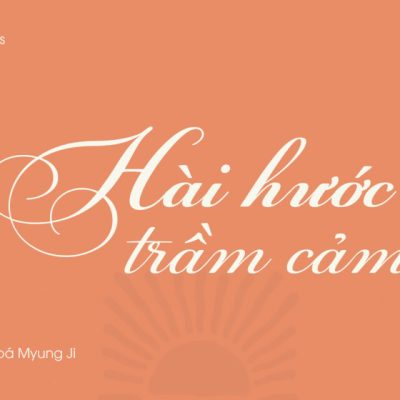
Giới thiệu về Font việt hoá MJ Monalisa
Trong thế giới đồ họa hiện đại, việc lựa chọn Font Chữ phù hợp đóng vai trò quyết định đến tính thẩm mỹ của sản phẩm. Font việt hoá MJ Monalisa là một bộ font mang phong cách script thanh lịch, tinh tế và cực kỳ sang trọng. Đây là lựa chọn hoàn hảo cho những ai đang tìm kiếm sự mềm mại nhưng vẫn giữ được nét hiện đại cho các dự án thiết kế của mình. Đặc biệt, phiên bản này đã được tối ưu hóa tiếng Việt hoàn chỉnh, giúp người dùng không còn lo lắng về lỗi hiển thị dấu.
Tại sao nên sử dụng Font việt hoá MJ Monalisa?
Bộ font này sở hữu những đường nét uốn lượn tự nhiên, tạo cảm giác như nét chữ viết tay nghệ thuật. Font việt hoá MJ Monalisa rất phù hợp để ứng dụng trong việc thiết kế thiệp mời, bìa sách, logo thương hiệu hoặc các ấn phẩm truyền thông học đường. Với khả năng tương thích cao trên nhiều phần mềm thiết kế như Photoshop, AI hay Canva, người dùng có thể dễ dàng tạo ra những tác phẩm độc đáo chỉ trong vài phút thao tác đơn giản.
Cách ứng dụng Font việt hoá MJ Monalisa hiệu quả
Để tận dụng tối đa vẻ đẹp của font, bạn nên kết hợp nó với các phông chữ không chân (sans-serif) để tạo sự cân bằng. Việc sử dụng Font việt hoá MJ Monalisa cho các tiêu đề lớn sẽ giúp thu hút ánh nhìn ngay lập tức. Ngoài ra, hãy chú ý đến khoảng cách giữa các chữ cái để đảm bảo văn bản luôn dễ đọc và thoáng đãng trên mọi giao diện hiển thị từ máy tính đến thiết bị di động.
Kết luận về bộ font nghệ thuật